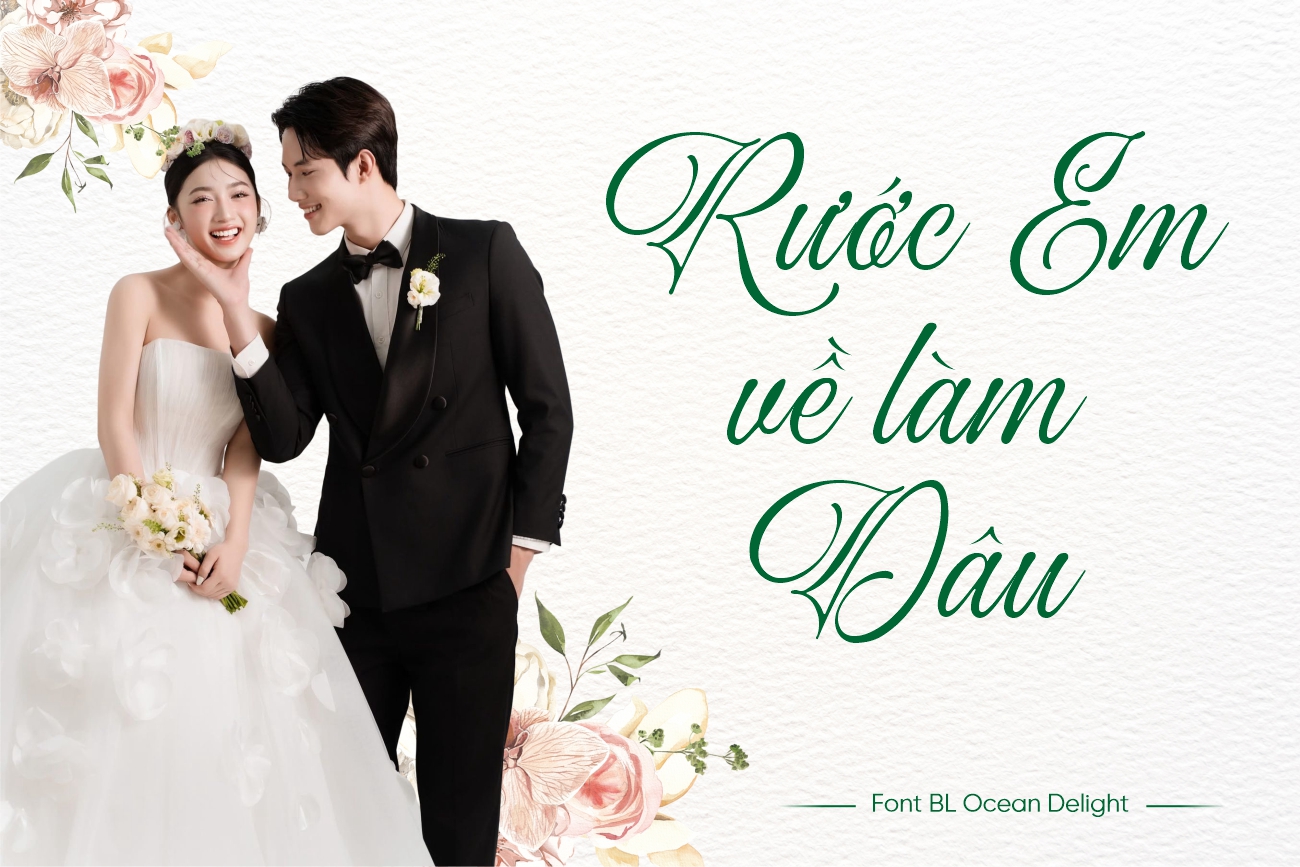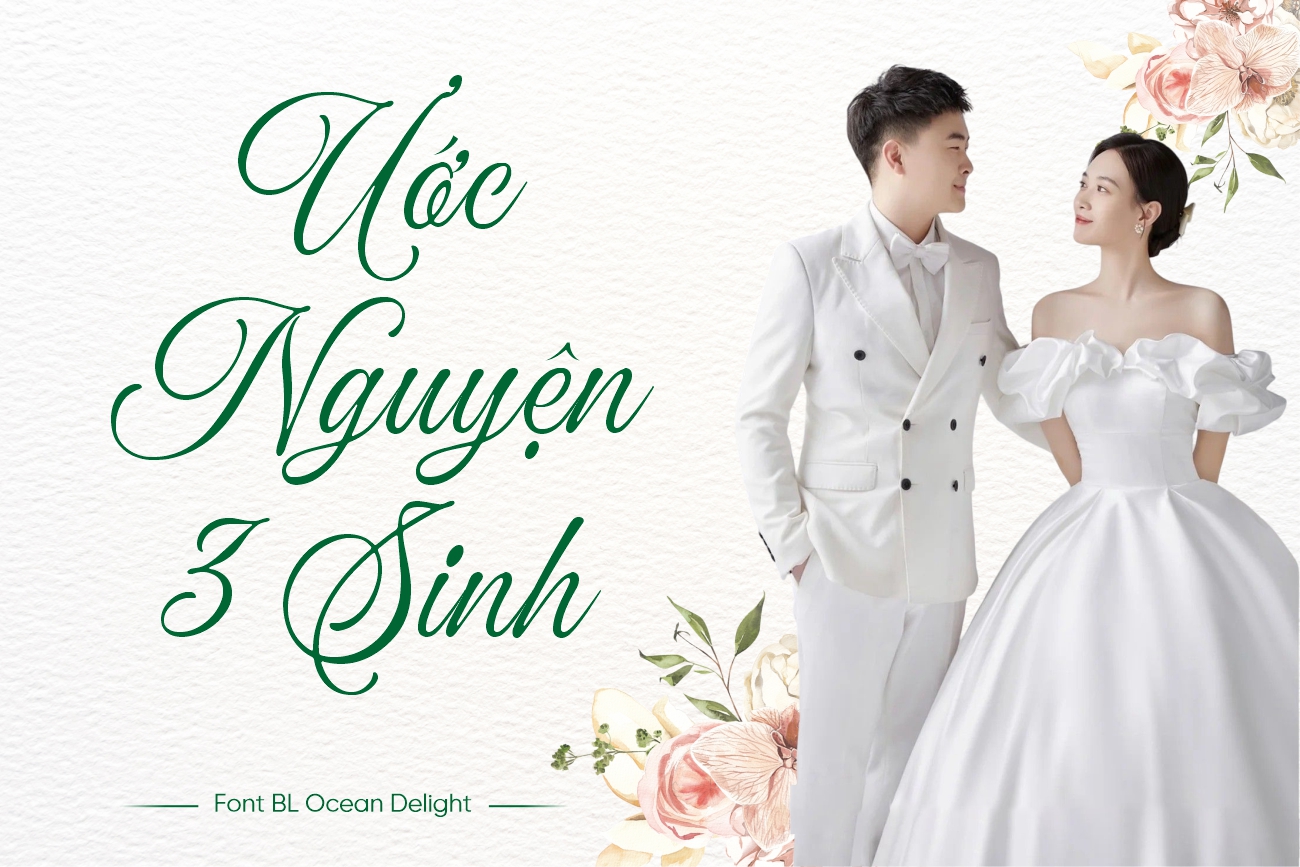
BL Ocean Delight – Phông chữ thiệp cưới đẹp và phong cách
Tác giả Blankids Studio
Việt hóa Font BL
BL Ocean Delight là phiên bản Việt hóa của font chữ Ocean Delight do Blankids Studio thiết kế, được Team BL chỉnh sửa và hoàn thiện để phù hợp với tiếng Việt. Nguyên bản Ocean Delight mang tinh thần nhẹ nhàng, bay bổng, lấy cảm hứng từ chữ viết tay và cảm xúc tự nhiên của con người. Khi được Việt hóa, font vẫn giữ nguyên vẻ đẹp mềm mại ban đầu nhưng được bổ sung đầy đủ dấu và ký tự, giúp sử dụng trơn tru trong các ấn phẩm tiếng Việt. Nhờ đó, BL Ocean Delight nhanh chóng trở thành lựa chọn lý tưởng cho những ai đang tìm kiếm một font chữ thiệp cưới vừa tinh tế vừa giàu cảm xúc.
Về kiểu dáng, BL Ocean Delight nổi bật ở sự uyển chuyển và nhịp nhàng của từng nét chữ. Các đường cong được xử lý mềm mại, có độ thanh – đậm tự nhiên như nét bút lướt trên giấy, tạo cảm giác gần gũi và chân thật. Tổng thể font thể hiện rõ sự kết hợp thẩm mỹ thư pháp cổ điển với nét hiện đại, phong cách, khi vừa giữ được tinh thần truyền thống của chữ viết tay, vừa có bố cục gọn gàng, dễ đọc và phù hợp với xu hướng thiết kế hiện nay. Chính sự dung hòa này giúp font không bị lỗi thời mà vẫn giữ được chiều sâu nghệ thuật.
Trong ứng dụng thực tế, BL Ocean Delight phát huy rất tốt vai trò của một font chữ thiệp cưới, đặc biệt với những thiết kế mang phong cách lãng mạn, nhẹ nhàng hoặc tối giản. Font cũng phù hợp cho thiệp mời, card cảm ơn, bìa album ảnh cưới, nhật ký, quote trang trí hay các ấn phẩm thủ công mang tính cá nhân. Khi xuất hiện trong bố cục tổng thể, các ký tự liên kết mượt mà, tạo dòng chảy thị giác tự nhiên, mang đến nhịp điệu thị giác vừa bình yên vừa tinh tế, giúp người xem cảm nhận được sự ấm áp và trân trọng trong từng chi tiết.
Xét về nguồn gốc, Ocean Delight là sản phẩm thể hiện rõ dấu ấn sáng tạo của Blankids Studio – nơi đề cao cảm xúc và tính thủ công trong thiết kế chữ. Qua bàn tay Việt hóa của Team BL, BL Ocean Delight không chỉ được tối ưu kỹ thuật mà còn được chăm chút về tỷ lệ và khoảng cách, đảm bảo tính thẩm mỹ khi sử dụng lâu dài. Sự kết hợp thẩm mỹ thư pháp cổ điển với nét hiện đại, phong cách giúp font dễ dàng thích nghi với nhiều bối cảnh thiết kế khác nhau. Với vẻ đẹp dịu dàng và chiều sâu cảm xúc, BL Ocean Delight là lựa chọn hoàn hảo cho những ai mong muốn tạo nên dấu ấn tinh tế, nhẹ nhàng nhưng đầy ý nghĩa trong các thiết kế mang tính kỷ niệm.